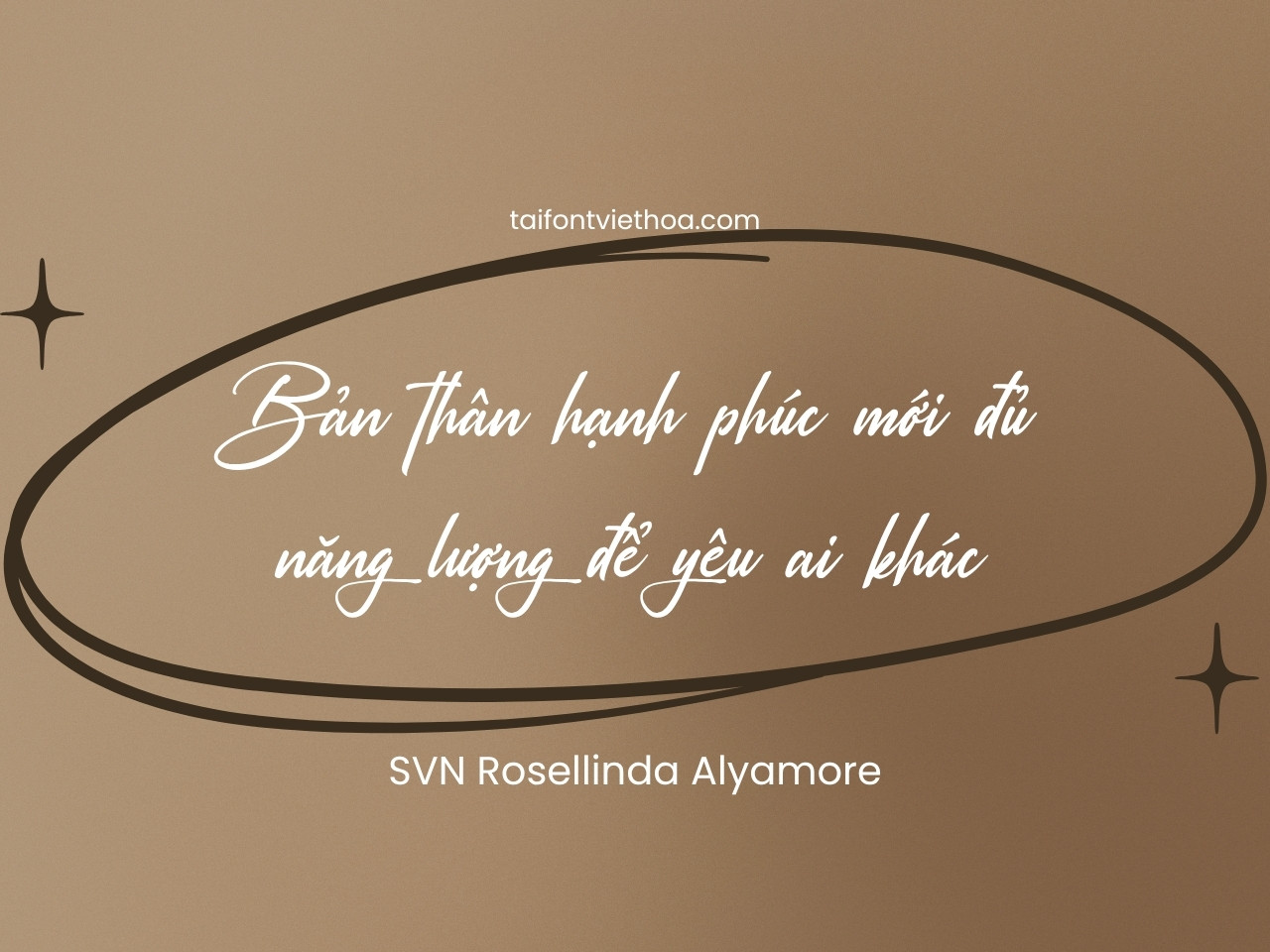
Giới thiệu về font SVN Rosellinda Alyamore – Kiểu chữ script viết tay sang trọng và lãng mạn
SVN Rosellinda Alyamore là phiên bản Việt hóa của font Rosellinda Alyamore – một kiểu chữ script mang phong cách viết tay tinh tế, bay bổng và đầy cảm xúc. Font được thiết kế dành cho các dự án yêu cầu sự sang trọng, cá nhân hóa và lãng mạn, thường được sử dụng trong thiệp cưới, lời mời, thương hiệu mỹ phẩm hoặc các thiết kế nghệ thuật. Font giữ nguyên nét mềm mại, uyển chuyển đặc trưng của bản gốc, phù hợp với các dự án cần sự tinh tế và duyên dáng.
Phiên bản Việt hóa được hoàn thiện bởi Taifontviethoa.com, hỗ trợ đầy đủ dấu tiếng Việt và hơn 80 ngôn ngữ khác, giúp nhà thiết kế dễ dàng ứng dụng trong các dự án sáng tạo tại Việt Nam, đặc biệt là trong lĩnh vực cưới hỏi, mỹ phẩm và thiết kế thương hiệu cao cấp.
Đường nét mềm mại, uyển chuyển – Lý tưởng cho thiệp cưới và thương hiệu mỹ phẩm
SVN Rosellinda Alyamore có cấu trúc script viết tay với các nét nối liền mềm mại, độ nghiêng nhẹ và các ligature tinh tế, tạo nên sự duyên dáng và sang trọng. Font mang lại cảm giác thân thiện nhưng không kém phần quý phái, rất phù hợp cho tiêu đề, logo, bao bì hoặc các phần thiết kế cần điểm nhấn nhẹ nhàng, bay bổng.
Ứng dụng lý tưởng: thiệp cưới, thiệp mời sự kiện, logo thương hiệu mỹ phẩm, bao bì sản phẩm cao cấp, bìa sách nghệ thuật, poster sự kiện và các dự án truyền thông cần phong cách tinh tế, nữ tính. Ngành nghề phù hợp: cưới hỏi, thời trang, mỹ phẩm, nghệ thuật, thiết kế sáng tạo và các thương hiệu định vị theo phong cách sang trọng, cá nhân hóa.